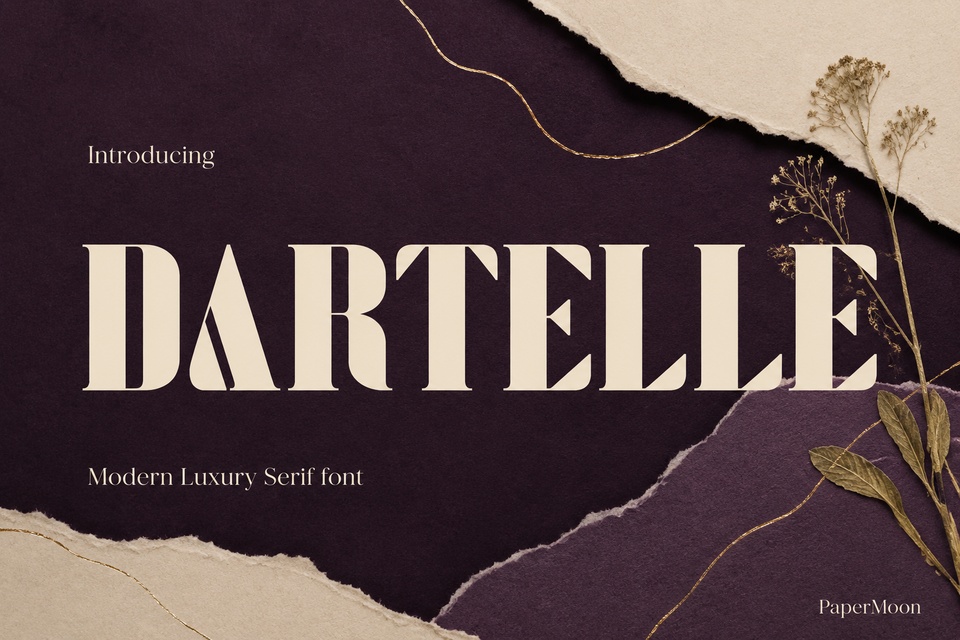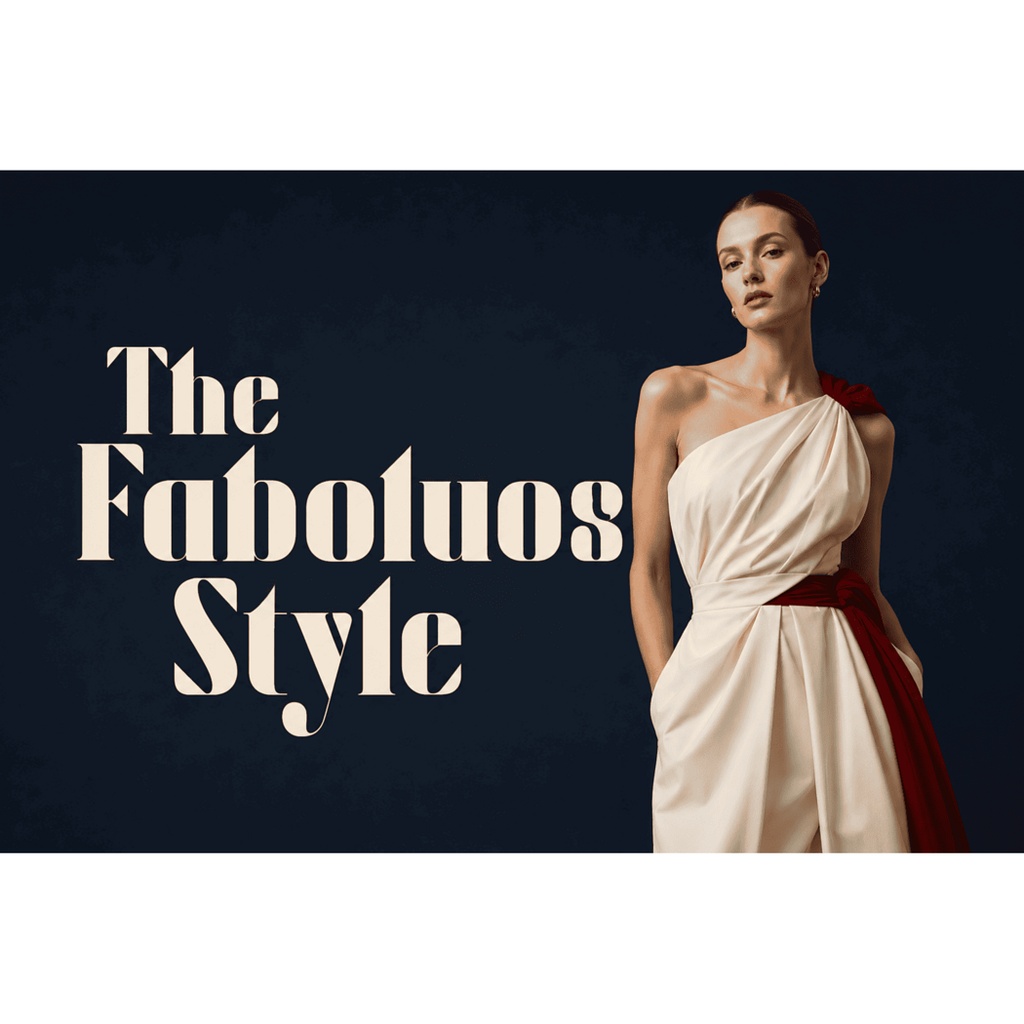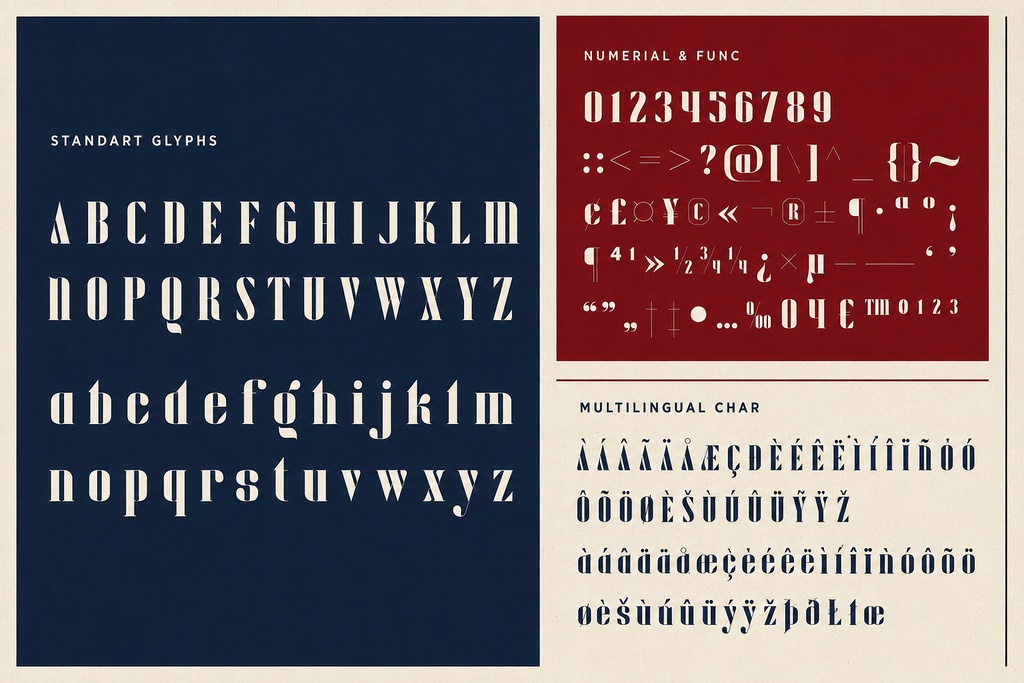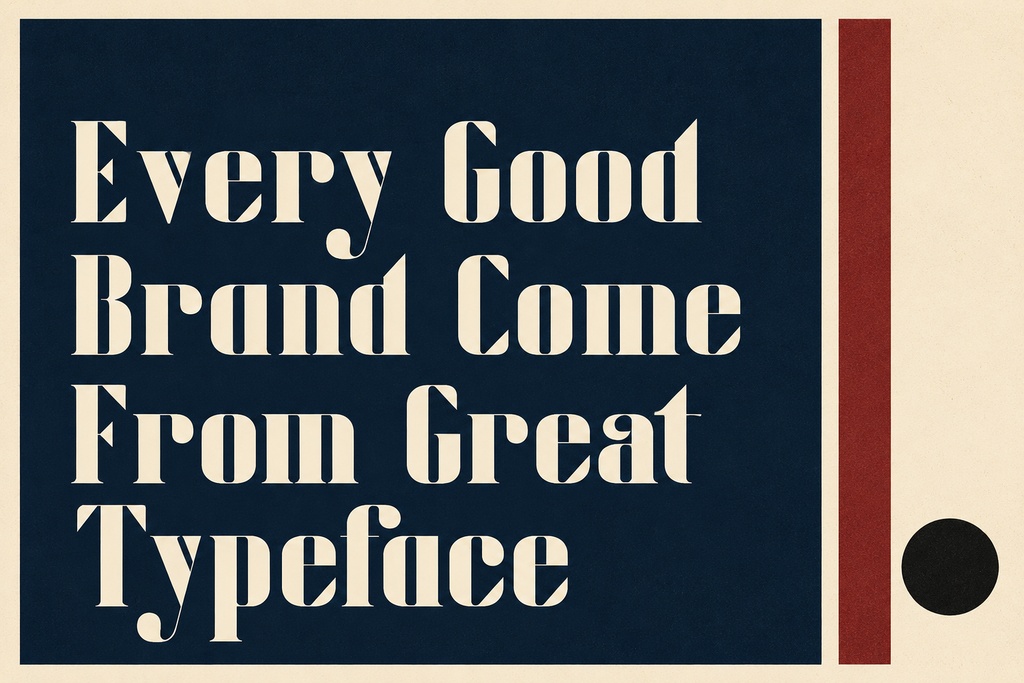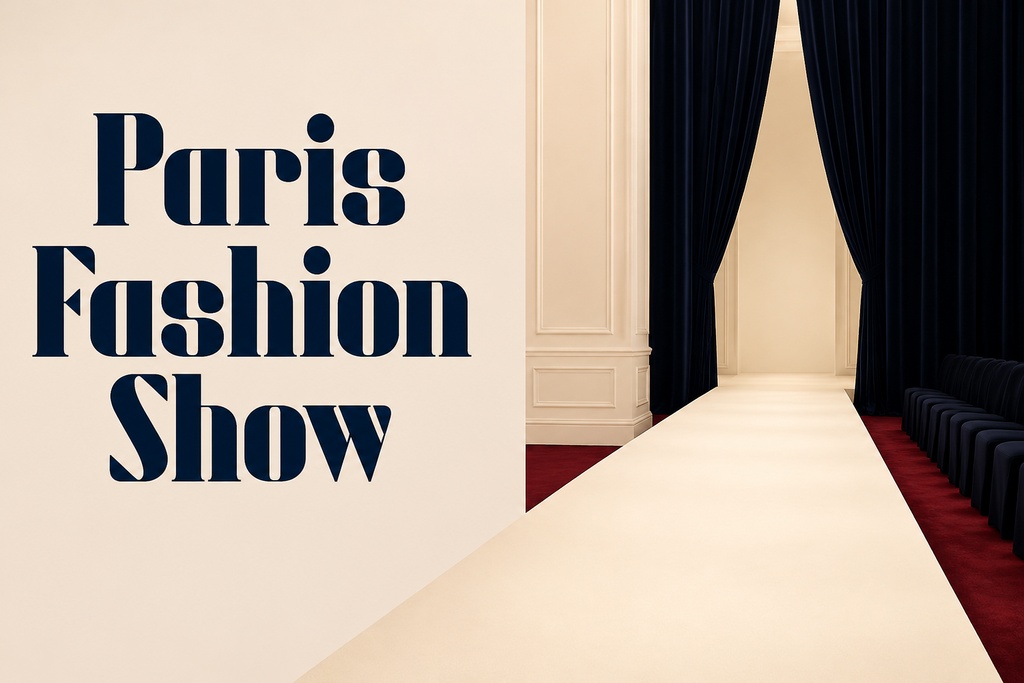
Dartelle - モダンで豪華なセリフ フォント デュオ
Dartelleは、洗練されたプロポーション、優雅なコントラスト、そして洗練されたエディトリアルな雰囲気を備えた、現代的でラグジュアリーなセリフフォントです。シックなライフスタイルブランドのブランディングやロゴタイプから、広告、ステーショナリー、プロダクトデザインまで、あらゆるクリエイティブな用途に適したプロフェッショナルな書体です。 このエレガントなセリフフォントは、あらゆるプロジェクトに洗練されたファッショナブルな印象を与え、控えめながらも確かな存在感で、あなたのデザインを際立たせます。 このラグジュアリーなセリフ書体には、**RegularとItalicの2スタイルによるFont Duo**が収録されています。ひとつのダウンロードで、ブランディングに必要なツールが揃います。Regularは、印象的なディスプレイ見出し、企業ブランドデザイン、ロゴロックアップなどに最適です。Italicは、エディトリアルデザイン、雑誌レイアウト、招待状などで、動きや強調を加えたい場合におすすめです。 各スタイルには、**291以上のグリフ**を収録。大文字・小文字、数字、句読点に加え、西欧言語で使用されるアクセント付き文字にも対応しています。 ### **主な特徴** * **Regular + Italicの2つのフルスタイル** — 堂々とした印象を与えるRegularと、動きやドラマ性を演出するItalic。 * **各スタイル291以上のグリフ** — フランス語、スペイン語、ドイツ語、イタリア語、ポルトガル語、オランダ語、スウェーデン語などに対応する西欧言語(Latin-1ベース)のアクセント文字を収録。 * **スタイル代替(ss01、ss02、salt、aalt)** — ロゴやディスプレイ用途で文字のデザインを切り替え、より個性的でハイファッションな印象を演出できます。 * **リガチャ(liga + dlig)** — 美しく洗練された文字の組み合わせにより、滑らかでプロフェッショナルなタイポグラフィを実現。 * **各スタイル4フォーマット、合計8ファイル** — OTF、TTF、WOFF、WOFF2を収録。印刷、Web、アプリデザインにそのまま使用できます。 * **クリーンなPaperMoonメタデータ** — インストール可能な埋め込み設定(fsType=0)、Copyright (c) 2026 PaperMoon。商用利用に対応しています。 ### **おすすめの用途** ラグジュアリーブランディング、企業ブランドアイデンティティ、ロゴタイプ・ロゴデザイン、エディトリアルデザイン、雑誌表紙、ファッション・ビューティーブランド、ハイエンドなウェディング招待状、ステーショナリー、広告・マーケティング、写真へのウォーターマーク、プロダクトデザイン、ラベル、パッケージデザイン、プレミアムなディスプレイタイポグラフィなど、エレガントなタッチが求められるあらゆるシーンで活躍します。 ### **対応ソフトウェア** **Adobe CC(Illustrator、InDesign、Photoshop)**、**Figma**、**Canva**、**Procreate**、**Affinity**、**Microsoft Word**に対応。OTF/TTFを読み込めるほぼすべてのアプリで使用できます。 WOFF/WOFF2のWebフォントは、`@font-face`を使用してWebプロジェクトに直接組み込むことができます。WindowsとMacのどちらでも簡単にインストールできます。 ### **ライセンス** 本商品は、Cubebrush Commercial Licenseに基づく**商用利用可能なライセンス**が付属しています。クライアントワークや販売する製品に使用でき、クレジット表記は必要ありません。 グリフのアウトラインはAIによって生成されたものではなく、手作業で制作されたオリジナルの書体です。そのため、商用プロジェクトにも安心してご利用いただけます。 あなたの次のラグジュアリーブランド、招待状、エディトリアルプロジェクトにふさわしい、エレガントなセリフの表現力を。 **Dartelleをカートに追加して、今すぐデザインを始めましょう。**